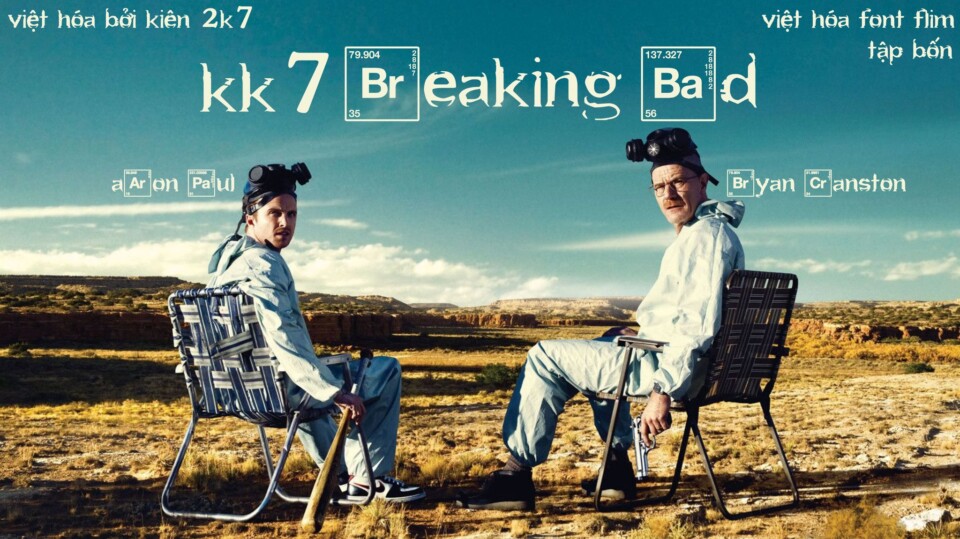
Font Việt hóa phim Breaking Bad – KK7-Breaking Bad
Giới thiệu về Font Việt hóa phim Breaking Bad – KK7-Breaking Bad
Nếu bạn là một người hâm mộ cuồng nhiệt của bộ phim truyền hình kinh điển Breaking Bad, chắc chắn bạn sẽ không thể quên được hình ảnh bảng tuần hoàn hóa học đầy ấn tượng trong phần tiêu đề. Để giúp các nhà sáng tạo nội dung tại Việt Nam dễ dàng tái hiện phong cách này, bộ Font Việt hóa phim Breaking Bad – KK7-Breaking Bad đã được ra đời. Việc sử dụng Font Miễn Phí chất lượng cao không chỉ giúp bản thiết kế của bạn trở nên chuyên nghiệp hơn mà còn tạo ra sự kết nối mạnh mẽ với người xem thông qua những hình ảnh quen thuộc.
Đặc điểm nổi bật của bộ font chữ này
Bộ font KK7-Breaking Bad được thiết kế mô phỏng hoàn hảo các ký hiệu nguyên tố hóa học với những đường nét vuông vức, mạnh mẽ và đậm chất kỹ thuật. Phiên bản Việt hóa này đã được tối ưu hóa hoàn toàn để hiển thị đầy đủ các dấu câu trong tiếng Việt mà không gặp lỗi hiển thị hay mất nét. Điều này rất phù hợp cho các bạn học sinh, sinh viên làm dự án về hóa học hoặc các designer muốn thiết kế poster, áo thun hay video theo chủ đề phim ảnh độc đáo.
Cách ứng dụng Font Việt hóa phim Breaking Bad – KK7-Breaking Bad hiệu quả
Với phong cách đặc trưng, bộ font này thường được sử dụng trong các tiêu đề lớn cần sự chú ý mạnh mẽ. Bạn có thể kết hợp các chữ cái đầu tiên trong tên mình để tạo thành một bảng tên theo phong cách “nguyên tố hóa học” cực kỳ sáng tạo. Sự kết hợp giữa màu xanh lá đặc trưng và các ô vuông trắng sẽ làm cho sản phẩm của bạn trở nên nổi bật và mang đậm dấu ấn cá nhân.